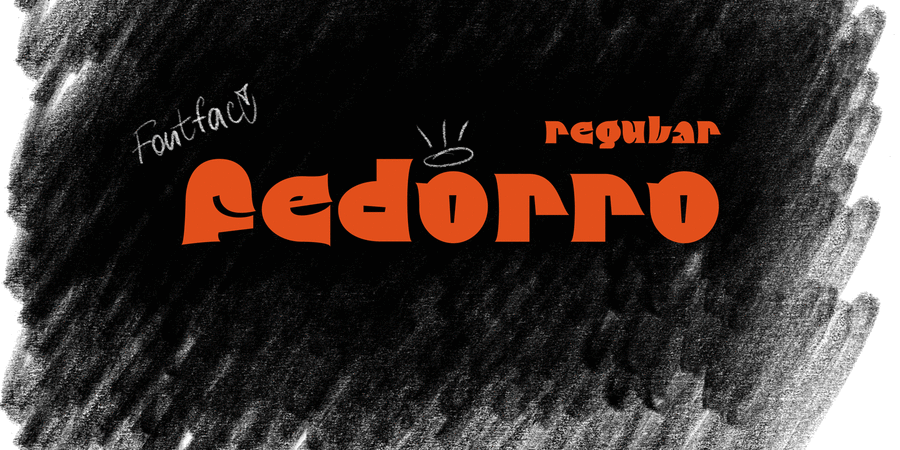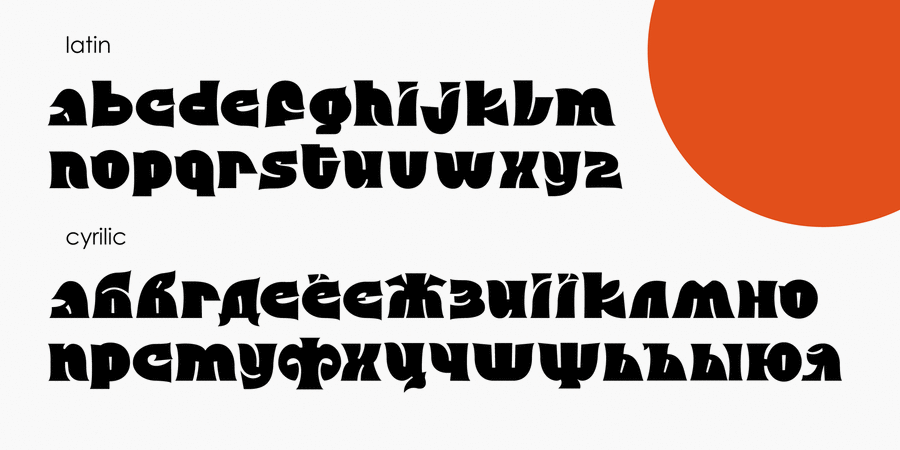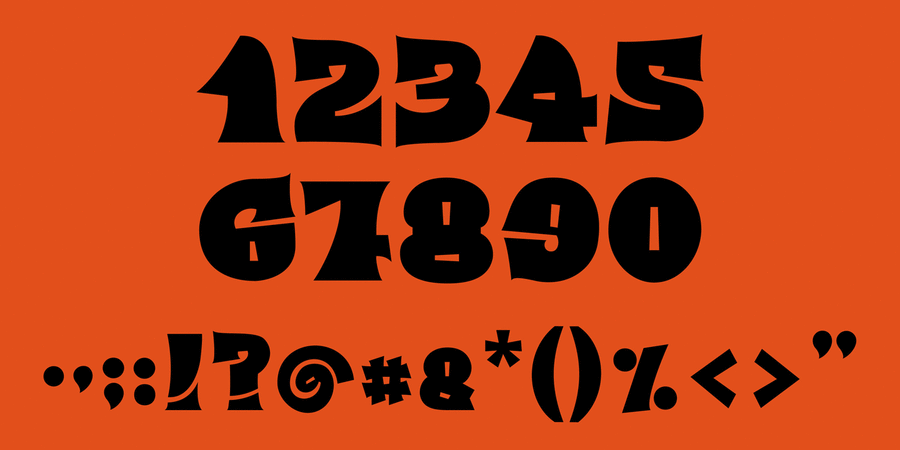
Це приклад сучасного українського стилю в дизайні букв. Літери заповнюють собою простір, не даючи змоги не звернути уваги на шрифт. Багато елементів було запозичено зі старовинних українських рукописних шрифтів, та перероблені на сучасний манер. Це дуже жирний шрифт з маленькими внутрішніми пробілами. Федорро можна використовувати в різному дизайні, наприклад: шрифтові плакати, обкладинки книг і журналів, заголовки, ініціали, логотипи, фірмовий стиль, етикетки, рекламні брошури, вивіски, сайти. Шрифт розробила Єлизавета Чепугова у 2020 році.
Асоціації з сімейством шрифтів FedorroОсобистість і характер гарнітури:
гострий, різкий, модний, сучасний, характерний, оригінальний, самобутній, помітний, грайливий, яскравий, гладенький, гнучкий, дивний, іронічний, виразний, радісний, живий, екзотичний, експериментальний, важкий, сильний, активний, товстий, цікавий, психоделічний